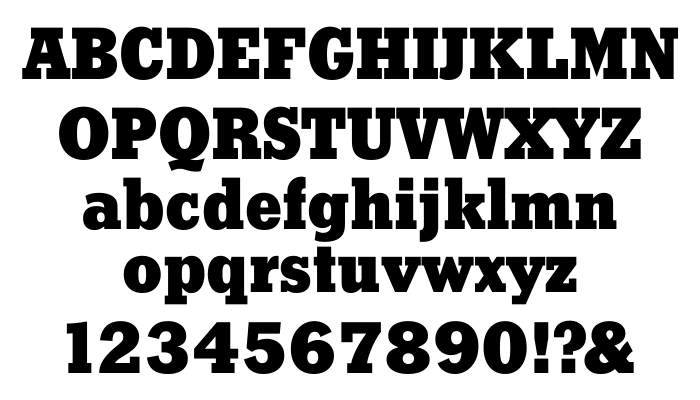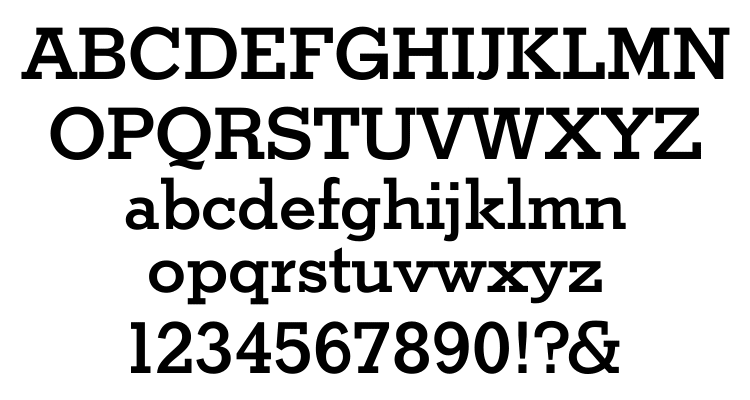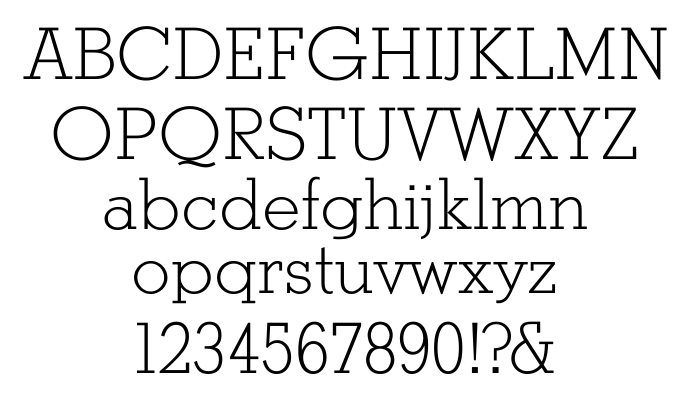
★Stymie
Designers
Morris Fuller Benton (1872–1948)
Date
1931
Foundry
American Type Founders (1892–1993)
Alternate
Light: A
Stymie Bold Condensed
Designer
Date
1937
Foundry
American Type Founders (1892–1993)
Stymie
Designer
Date
Foundry
スラブセリフの定番フォント「スタイミー」。 デジタル版の Black は 写植版の Extra Bold に該当する。 Stymie Obelisk がある。